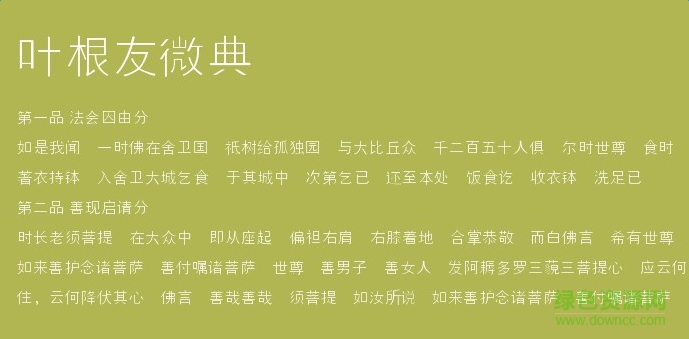
葉根友微典字體是一款簡(jiǎn)約細(xì)黑風(fēng)格字體軟件,微典體是葉根友字體系列中比較細(xì)膩的一款字體,字體筆畫猶如發(fā)絲,非常清新脫俗,還有更多好看字體歡迎來(lái)綠色資源網(wǎng)下載體驗(yàn)!
葉根友微典字體是一款正文標(biāo)題字體,適用于時(shí)尚品牌設(shè)計(jì)和內(nèi)容簡(jiǎn)介,其獨(dú)特的波浪藝術(shù)風(fēng)格別具特色!
該字體筆畫細(xì)膩,每個(gè)字體所占空間一致,給人非常清爽簡(jiǎn)單的感覺(jué),非常的好看!